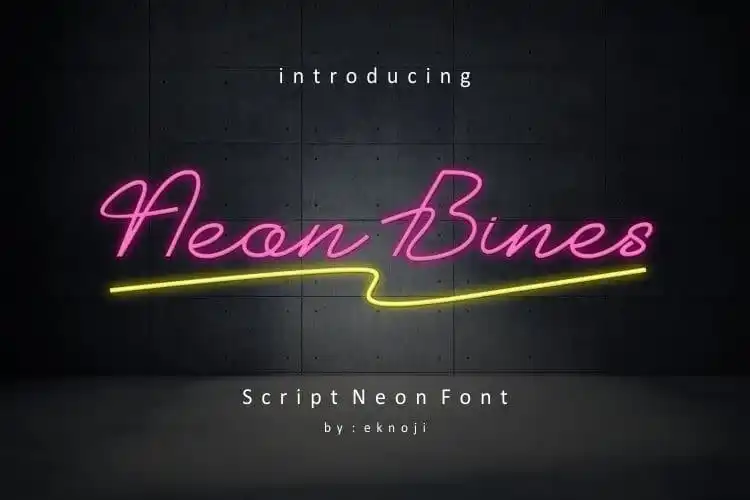
Neon Bines Handwritten Font – Fonte Grátis
Neon Bines Handwritten Font
A Neon Bines Handwritten Font é uma maravilha criada por designers habilidosos que expressa sua essência única através do estilo de fontes script. Feita a mão, esta fonte traz um ar inovador e autêntico para qualquer projeto, especialmente os que exigem elegância e sofisticação. Seja para criar uma identidade visual forte e memorável, decorar o seu casamento ou até mesmo personalizar sua marca em redes sociais, essa fonte é perfeita. Ideal tanto para o design de logotipos e marcas quanto para cartas de convite, materiais de decoração, criações de casamentos, desenhos para exibição, postagens na mídia social, anúncios, embalagens dos produtos, designs das mercadorias, etiquetas, fotografia ou até mesmo imagens com efeito de água, a Neon Bines oferece uma variedade impressionante de possibilidades. E embora seu estilo seja claramente influenciado por fontes script, sua personalidade única faz dela um recurso visual que se destaca em qualquer projeto.